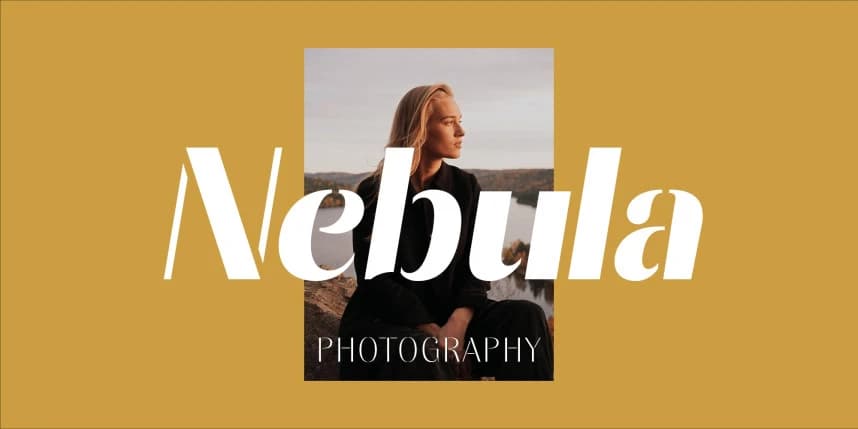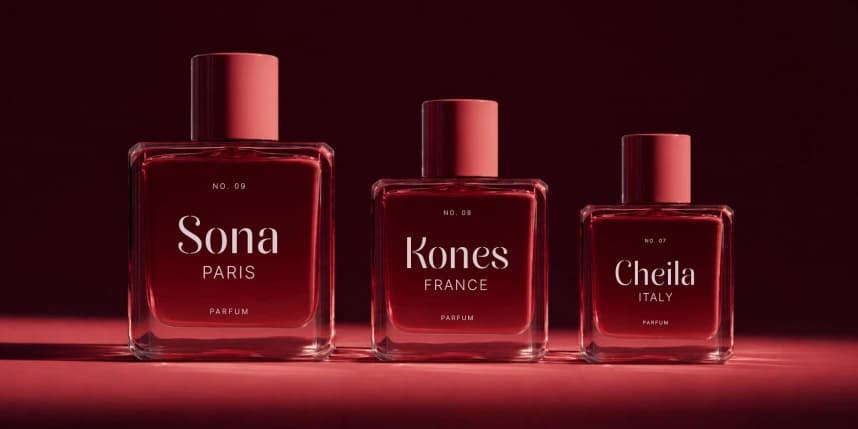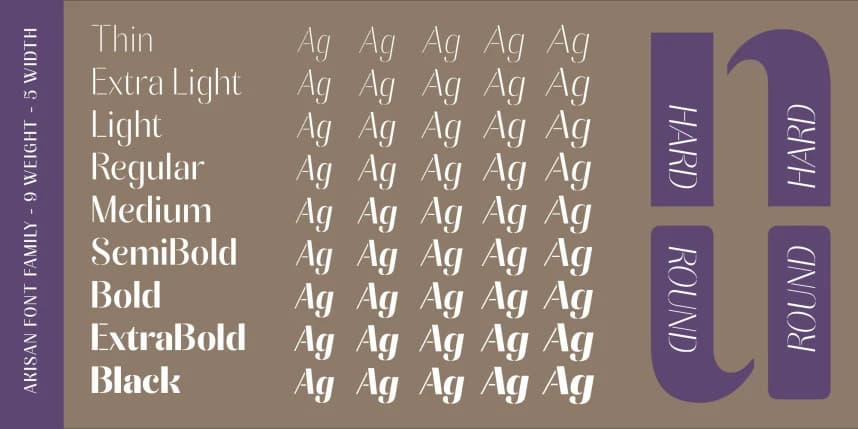
Akisan Font Family
Akisan Font Family, editoryal zarafeti temiz, çağdaş bir görünümle birleştiren modern bir sans serif stencil yazı tipidir. Harf biçimleri ince kontrast, dengeli oranlar ve ayırt edici ayrıntılar içerir; bunlar güçlü bir görsel kimlik yaratırken netliği de korur.
Akisan Font Family, editoryal zarafeti temiz ve çağdaş bir dokunuşla harmanlayan modern bir sans serif stencil yazı tipidir. Harf biçimleri ince kontrast, dengeli oranlar ve belirgin ayrıntılar sergiler; bunlar netliği korurken güçlü bir görsel kimlik oluşturur.